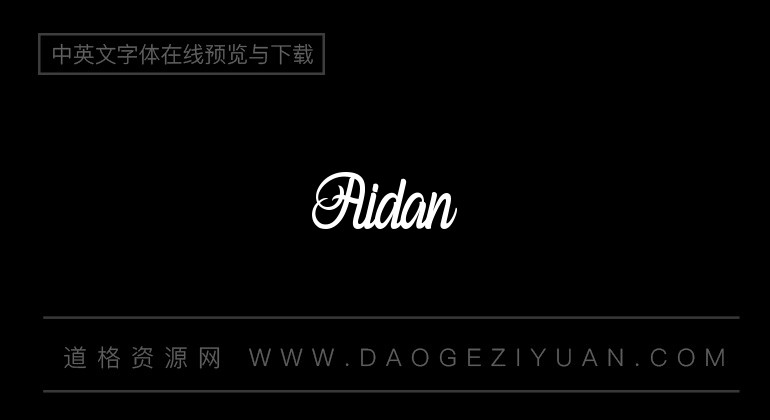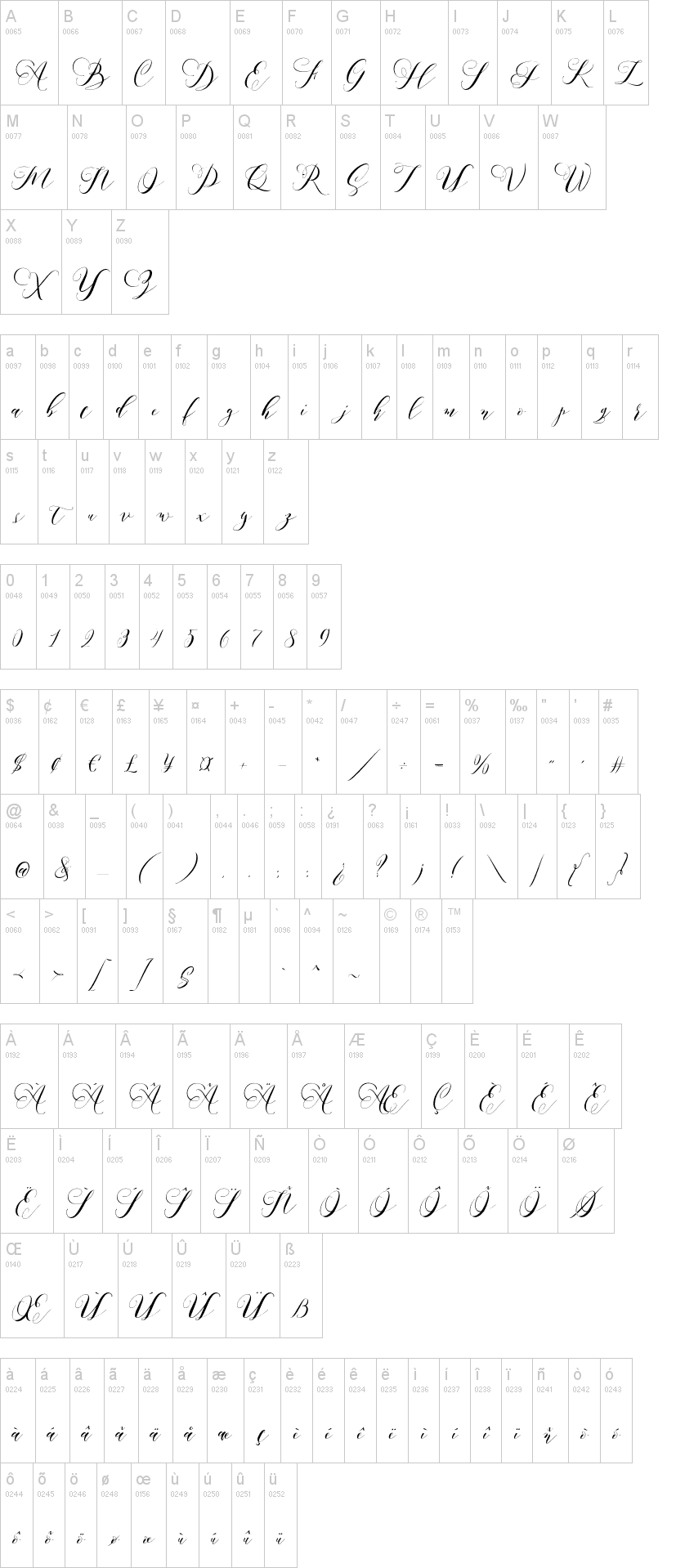
Aidan
Aidan 是一款由英国设计师 Craig Black 创作的手写字体。它是一款精致而古典的手写字体,可以让你的文案更加有个性。它具有自然而优雅的笔画,可以为你的文案增添一份温柔和温情。Aidan 字体特别适合用于浪漫的文案,可以让你的文案更加柔和而温暖。
Aidan是一款非常不错的手写艺术字体,具有很好的视觉感,适合于文化类的宣传设计、商业类品牌的广告和产品包装设计以及个性化文字排版等较多场景。